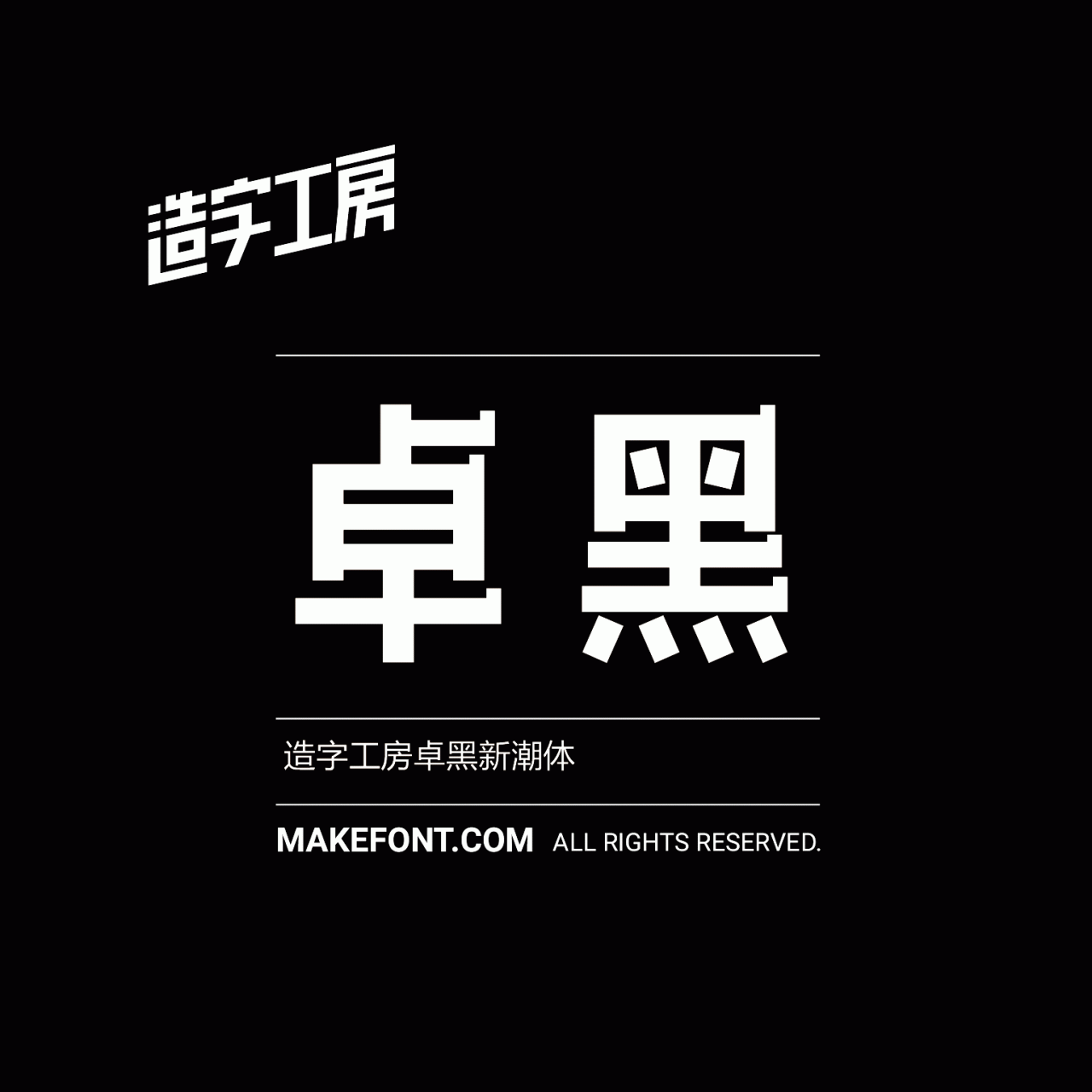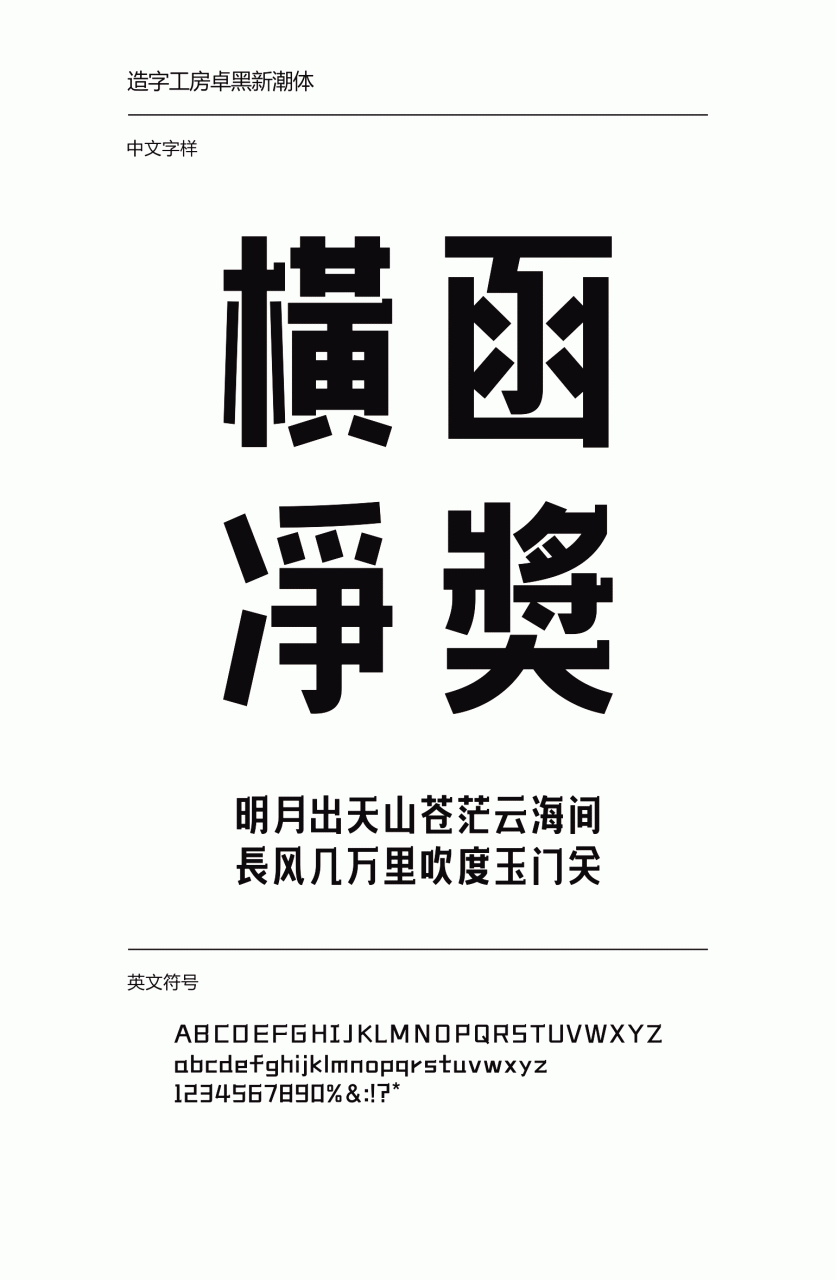
造字工房卓黑新潮体
造字工房卓黑新潮体,字形瘦长,笔画平直,其风格雄强正肃,引人注目。字形结构严谨,实用性强,横画上的方形凸起处理,令字形个性鲜明,更显凝练正则之势。适用于大标题及个性品牌设计推广等环境。本字库在保留其简体字形风格的同时参考旧字形结构、笔画特点,进行了大胆创新及识别性的中和处理,使其有更大的应用空间。本字库采用OpenType/CID格式,Adobe-GB1-5编码。基于中华人民共和国GB2312-80字符集标准,另按需添加101个汉字。共收容字数6864CJK汉字,ASCII常用字符100个。